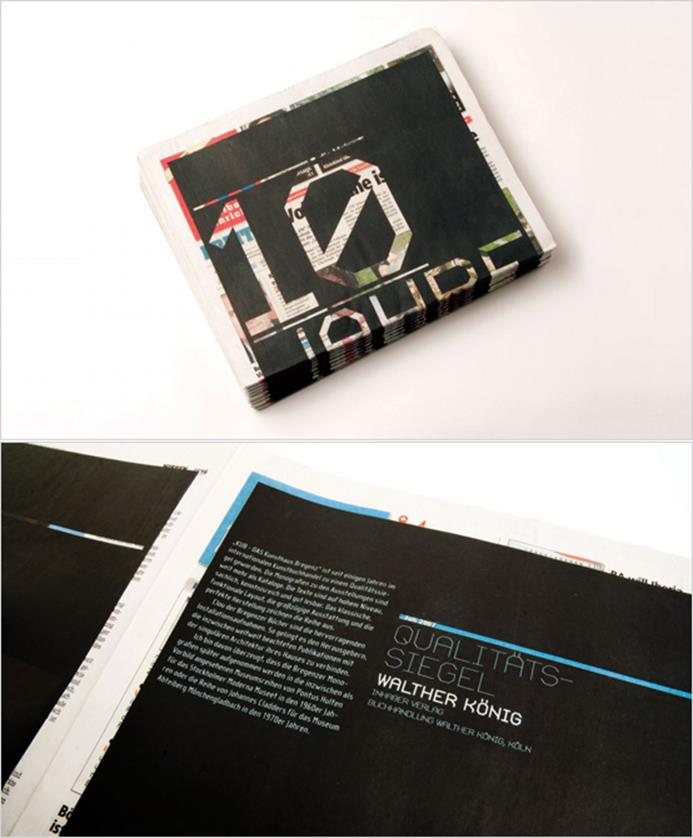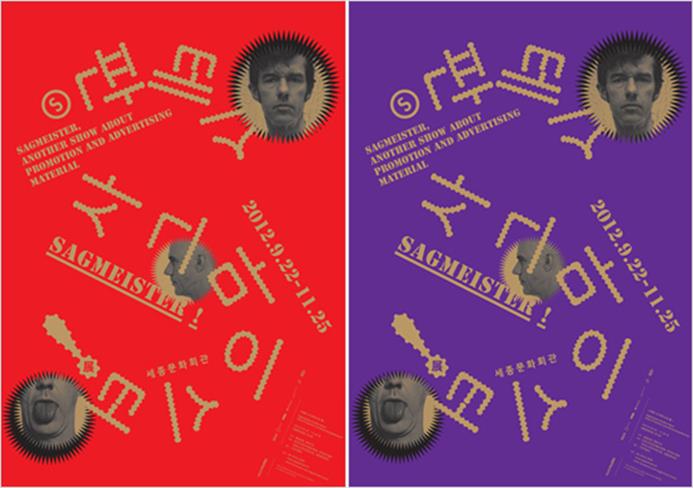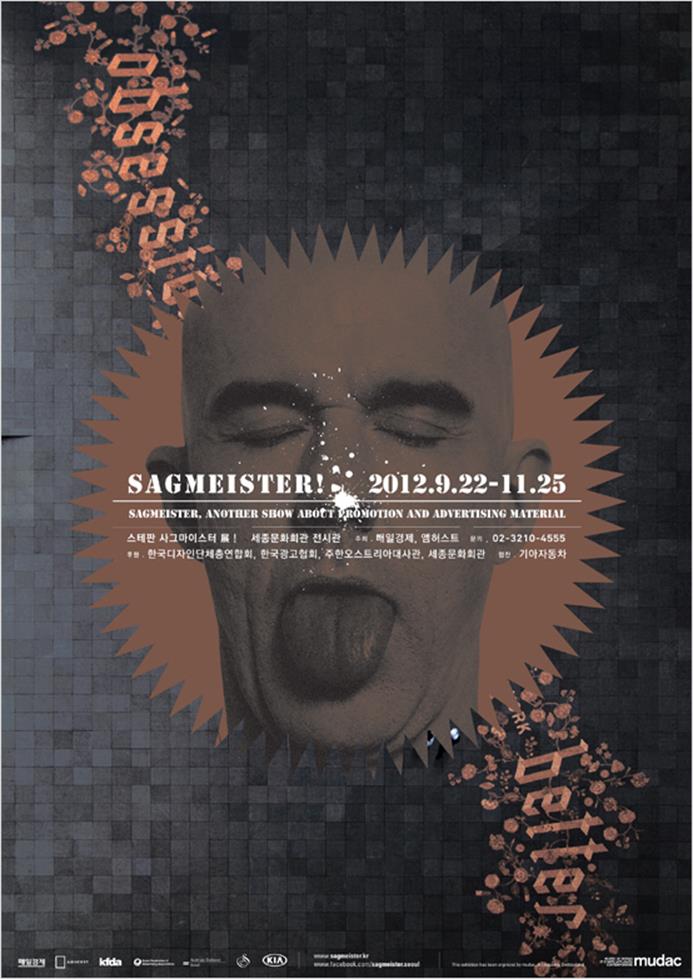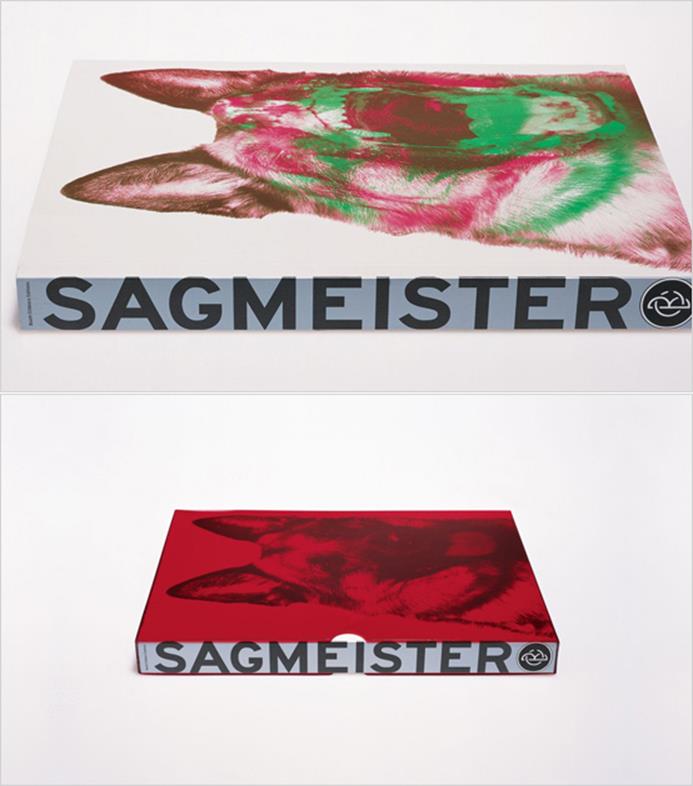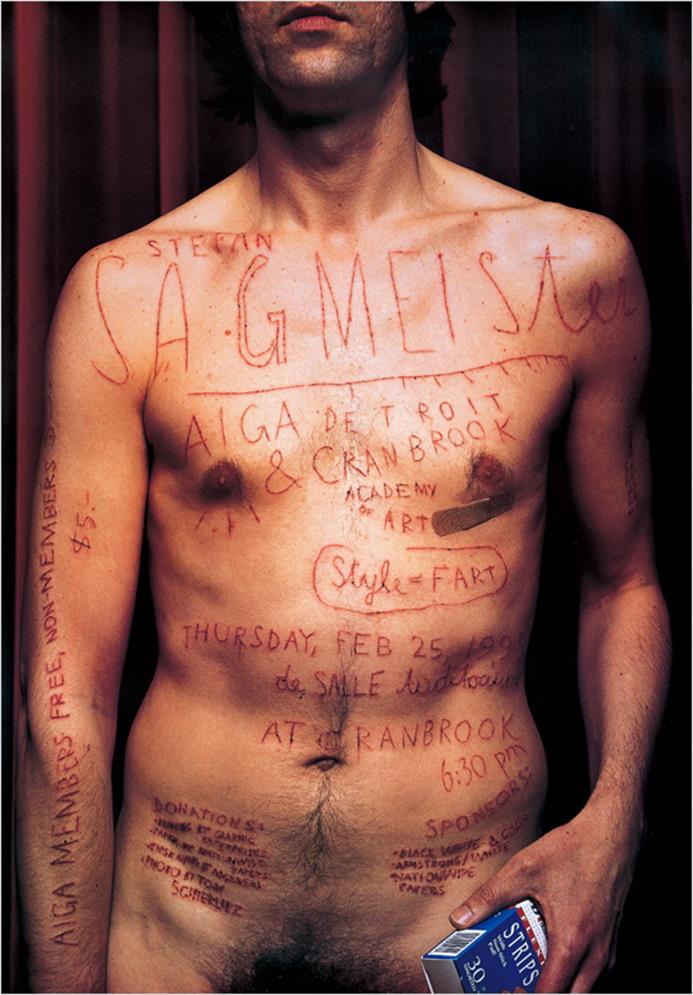
사그마이스터_1.인터뷰
스테판 사그마이스터(www.sagmeister.com)의 일상과 작업, 디자인 철학에 대한 이야기를 들어볼 수 있는 인터뷰를 시작으로 그의 대표작들과 국내에서 진행된 사그마이스터 강연 내용을 정리해 3회에 걸쳐 소개한다.
스테판 사그마이스터는 1962년 오스트리아 브레겐츠(Bregenz)에서 출생했다. 비엔나의 응용예술 대학교에서 그래픽 디자인을 전공하고 1987년 뉴욕으로 이주한 사그마이스터는 풀브라이트 장학금(Fulbright Scholarship)을 받고 프랫 인스티튜트(Pratt Institute)를 다니기도 했다. 29세에 광고대행사 레오버넷(Leo Burnet) 홍콩에서 일을 시작하고 1993년에 뉴욕으로 돌아온 그는 엠앤코(M & Co.)에서 헝가리 출신의 그래픽 디자이너 티보 칼맨(Tibor Kalman)과 함께 일하게 되었다. 같은 해 스튜디오가 문을 닫게 되면서 사그마이스터는 자신의 스튜디오 ‘Sagmeister Inc.’를 설립했다.
사그마이스터는 1994년 작업한 3인조 록 밴드 에이치피 징커스(H. P. Zinkers)의 앨범 <Mountains of Madness> 커버 작업으로 그래미상 후보에 오르면서 본격적으로 알려지게 되었다. 이듬해부터 그는 데이비드 번(David Byrne), 루 리드(Lou Reed), 롤링스톤즈(Rolling Stones)와 같은 영향력 있는 아티스트들의 앨범 커버를 디자인하기 시작했다. 1996년부터 미국 그래픽아트 협회(American Institue of Graphic Arts)인 ‘AIGA’ 포스터를 디자인하기 시작했다. 1년에 하나씩 총 세가지 포스터를 제작했다. 한편, 사그마이스터는 2000년부터 ‘안식년’을 갖기로 결정하고 자신의 스튜디오에서 했던 모든 상업적인 작업의뢰를 받지 않으면서 자신만의 실험적인 프로젝트에 집중하는 1년의 시간을 갖는 것으로 유명하다. 그는 7년마다 안식년을 보내고 있다.
하루 중 가장 기분 좋은 순간은 언제인가요?
초저녁과 이른 아침입니다. 디자인 작업을 하기에 가장 좋은 순간은 이른 아침이에요. 그 시간에 사무실은 가장 조용합니다. 그 시간이야말로 콘셉트에 대해 진지하게 생각할 수 있는 순간입니다. 반면에 저녁이 좋은 이유는 하루 일과를 끝내고 즐길 수 있는 시간이기 때문이에요. 특히 해야 할 모든 일을 완전히 마쳤을 때는 더욱 좋겠죠.
많은 작업들이 음악과 관련 있습니다.
저는 항상 음악에 관심이 많았습니다. 이젠 나이가 들어서 제 삶에서 음악이 차지하는 비중이 점점 줄고 있긴 하지만, 23살 무렵 제게 음악은 지금보다 훨씬 더 큰 의미였습니다. 오스트리아에서 살았을 때는 라디오를 즐겨 들었습니다. 하지만 뉴욕에서는 별로 듣지 않고 있어요. 음악과 음악 사이에 나오는 광고가 저를 미치게 만들기 때문이죠. 요즘엔 애써 라디오 채널을 돌려보지도 않습니다. 우리 사무실은 새로 들어오는 인턴에게 평소 즐겨 듣는 음악을 가져오도록 부탁합니다. 이제는 인턴이 해야 할 전통처럼 자리를 잡았죠.
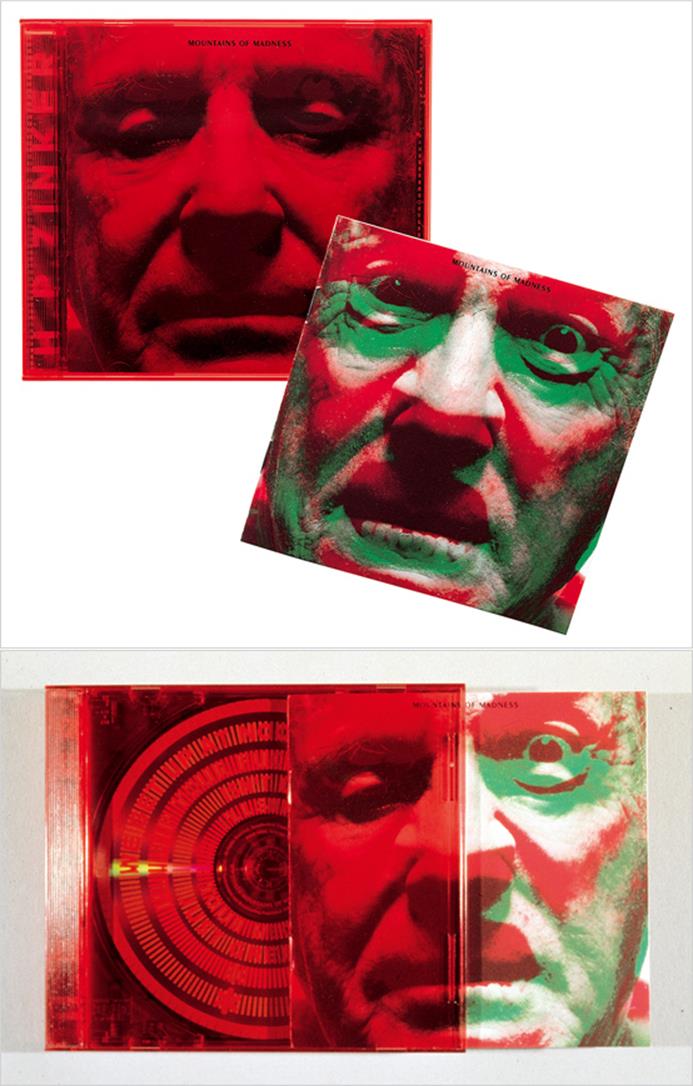
<Mountain of Madness> 음반 디자인.
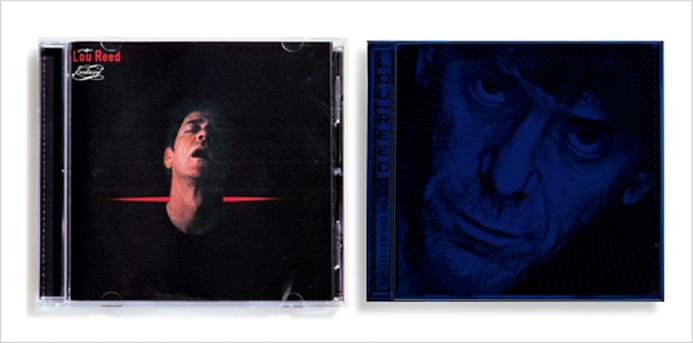
루 리드 음반 디자인.
사그마이스터는 1994년 작업한 3인조 록 밴드 에이치피 징커스(H. P. Zinkers)의 앨범 커버 작업 이후 데이비드 번(David Byrne), 루 리드(Lou Reed), 롤링스톤즈(Rolling Stones)와 같은 유명 아티스트의 앨범 커버를 디자인하기 시작했다.
함께 작업하는 밴드의 음악을 항상 좋아하나요?
우리는 뮤지션이든 다른 어떤 고객이든 싫어하는 사람과는 일을 하지 않으려고 합니다. 바보들과 일해야 할 이유는 전혀 없어요.
침대 옆에 어떤 책들을 두고 보는지 궁금합니다.
저는 폴 오스터(Paul Auster) 책을 좋아하는데, 그가 쓴 <브루클린 풍자극(The Brooklyn follies)>을 이제 막 다 읽었습니다. 지난 주에는 피카소의 전기를 읽었고, 지금은 존 크로포드의 <최후의 진실(The Last Truestory I’ll ever tell)>을 읽기 시작했습니다. 이 책은 1999년 이라크 전에 참전한 한 군인의 기록인데, 저는 실화라면 뭐든지 정말 좋아합니다. 소설은 그냥 재미로 읽고 있어요. 디자인 잡지는 스튜디오에서는 몇 권을 구독하고 있지만 재미 삼아 넘겨볼 뿐 그 안에서 영감이나 아이디어를 얻지는 않습니다. 더군다나 일하는 시간에는 전혀 보지 않습니다.
그러면 새로운 뉴스는 어떻게 접하나요?
텔레비전은 절대 아닙니다. 저는 미국의 TV 뉴스를 참을 수 없습니다. 대신 <뉴욕타임즈>를 읽습니다. 관점이 편향적이기는 하지만 저는 <뉴욕타임즈>가 꽤 좋은 신문이라고 생각합니다. 이것이 아마 저의 주 소식통일 거에요.
작업은 주로 어디에서 하나요?
어디에서든 가능해요. 제작은 주로 사무실에서 하지만, 아이디어나 콘셉트를 구상하는 것은 어디에서든 할 수 있습니다. 저는 여행을 많이 다니는데, 비행기 안에서 일하는 것도 생각보다 편하고, 호텔방에서 작업하는 것도 괜찮아요. 저는 새로운 환경이나 처음 가보는 나라에서 작업하길 좋아합니다. 그리고 자유롭게 일할 수 있는 환경에서 마감에 쫓기지 않고 작업할 수 있는 프로젝트를 선호하죠.
작업에 대해 다른 그래픽 디자이너들과 토론하는지 궁금합니다.
저는 ‘두 번째 화요일(Second Tuesday)’이라는 그룹의 멤버입니다. 디자인 회사를 운영하고 있는 15명 정도의 디자이너들이 두 달에 한번 모임을 가지고 있는데요. 멤버 중 누군가의 집이나 스튜디오에서 돌아가며 모이고, 장소를 제공하는 사람이 저녁과 토론 주제를 준비합니다. 재정 문제 같은 굉장히 현실적인 주제로 토론하기도 하죠. 최근에는 확실히 문화적 이슈보다 경영과 사업 이슈로 더 초점이 맞춰지고 있습니다.
당신의 디자인 스타일에 대해 친구가 설명한다면 어떻게 묘사할 수 있을까요?
오랫동안 저는 한 가지 스타일로 작업해오지 않았다는 점에 자부심이 있습니다. 하지만 그 한가지를 고수하는 건 점점 더 어려워지고 있어요. 매 프로젝트마다 스타일을 바꾸기 위해 어떤 역사적 스타일이나 어느 디자이너의 스타일을 모방하지 않으면서 매주, 매달 간격으로 쏟아지는 새로운 작품들을 따라 잡기는 거의 불가능에 가깝기 때문이죠. 결국 스타일로 제 작업을 설명할 수는 없다고 생각합니다. 오히려 저는 우리 스튜디오의 명성이 수작업 퀄리티에 있다고 봅니다.
‘스타일은 허풍(fart)’이라고 말하기도 했죠.
네, 그렇게 말했습니다. 하지만 그 얘기도 결국 관두게 되었어요. 어떤 이론의 표제였는데 스타일과 스타일적인 질문들은 그저 ‘소리만 크게 나는 방귀 같은 허풍일 뿐 의미가 없다’는 뜻이었습니다. 하지만 결국 그렇지 않다는 것을 깨닫게 되었습니다. 어떤 가치 있는 콘텐츠가 있다면 이를 적절한 형식과 스타일로 표현하는 것 역시 매우 중요하다는 사실을 뒤늦게 경험했죠. 스타일은 콘텐츠를 소통시키는 매우 유용한 도구일 수 있습니다. 이제는 더 이상 스타일이 허풍이라고 생각하지 않습니다.
가장 만족스러웠던 프로젝트는 무엇인가요?
돌려서 말하자면 훌륭한 제품이나 서비스를 보유한 좋은 고객들과 함께 한 프로젝트라고 할 수 있습니다. 예를 들면, 제가 좋아하는 밴드의 CD 커버나 함께 일하기 좋은 친절한 클라이언트들, 그리고 저보다 똑똑해서 배울 점이 많은 클라이언트들이 되겠죠.
Sagmeister & Walsh(www.sagmeister.com)
사그마이스터는 19년간 유지해온 스튜디오 ‘Sagmeister Inc.’를 지난 6월 ‘Sagmeister & Walsh’라는 이름으로 변경했다.
제가 항상 함께 일하고 싶어서 어떻게든 기회를 만들어보려고 노력했던 사람이 있다면, 위대한 프로그레시브 밴드인 킹 크림슨(King Crimson)의 기타리스트 로버트 프립(Robert Fripp)입니다. 16살 때부터 숭배해오던 밴드에요. 제품 쪽으로는 코카콜라 캔을 새롭게 디자인한다거나, 진짜 ‘세계적인’ 브랜드의 아이덴티티 디자인 등 뭔가 강력한 영향력을 지닌 거대한 프로젝트에 도전해보고 싶습니다. 사실 거대한 프로젝트를 우리 스튜디오 같은 소규모의 디자인 회사나 개인 디자이너들이 멋지게 해낸 전례는 없어요. IBM이나 코카 콜라처럼 말입니다.
그럼에도 불구하고 지난 10년간 규모가 큰 프로젝트일수록 거의 거대 브랜딩 컨설팅 회사로 넘어가고 있는 추세입니다. 그런 회사들은 프로젝트나 디자인의 목표 자체가 다르기도 하겠지만, 제가 보기에는 그야말로 엉망진창입니다. 물론 언제나 몇몇 예외는 있지만 말이죠. 물론 이는 디자이너들이 거대한 프로젝트를 기피하는 까닭도 있어서 더 안타까운 일입니다. 오늘날의 아이들은 이러한 디자인 환경 속에서 세상을 배워나가기 때문입니다. 어쨌거나 큰 회사는 큰 회사와 일을 하고 싶어하기 때문에, 소규모 스튜디오에서 거대한 프로젝트를 맡기란 정말 하늘의 별 따기가 되어버렸습니다.
역사 속 디자이너 중 높게 평가하는 사람이 있다면 누구인가요?
제 옛 상사인 티보 칼맨입니다. 아직 활동 중인 사람 중에 꼽아야 한다면 한도 끝도 없을 거에요. 제품 디자인 분야에서는 마르셀 반더스(Marcel Wanders)를 위시한 네덜란드 디자이너들이 괜찮다고 생각합니다. 그래픽 분야 중 미국에서는 릭 발리첸티(Rick Valicenti), 영국에서는 마크 패로우(Mark Farrow)를 꼽을 수 있지만 그 외에도 아주 많습니다.
사그마이스터의 무정부주의적인 면모는 그에게 명성을 가져다 주었고, 앞서 언급한 루 리드, 롤링스톤즈, 토킹헤드와 같은 유명한 아티스트와 함께 일할 수 있는 기회를 주었다. 그의 초기 작업은 의도적으로 공격적이면서 기교를 배제한 거친 타이포그래피로 가득 차 있고, 분해한 옷으로 만들거나, 자필로 쓴 문자들이 주를 이룬다. 비꼬는 듯한 유머와 가끔 알몸을 노출하는 등의 돌출 행동에 가려지는 듯 하지만, 그럼에도 불구하고 사그마이스터의 컨셉화 하는 능력은 빛이 난다. 그가 보여주는 최근 작업의 콘셉트는 점점 더 정제되고 있다. 그래서 그의 최근 결과물들은 과거의 작업들보다 훨씬 더 세련되고, 다각적이며, 풍자적이다. 오스트리아 브레겐츠 쿤스트하우스(Kunsthaus Bregenz)의 10주년 기념 신문을 진두 지휘한 디자이너 또한 사그마이스터였다.
미래에 대해 걱정하는 것들이 있다면 무엇인가요?
별로 없습니다. 제가 대단한 사람은 아니지만 그렇다고 미래가 불안하다거나 걱정스럽지는 않습니다. 지금 사람들이 걱정하는 모든 문제들은 결국에 잘 풀릴 거라 생각합니다. 인간은 어떤 상황에나 적응할 수 있고, 저는 지금 현재가 꽤 살기 좋은 세상이라고 생각합니다.
마지막으로 젊은이들에게 해주고 싶은 조언이 있다면요?
“좋은 사람이 되려고 노력하라. 그리고 열심히 일하라.”